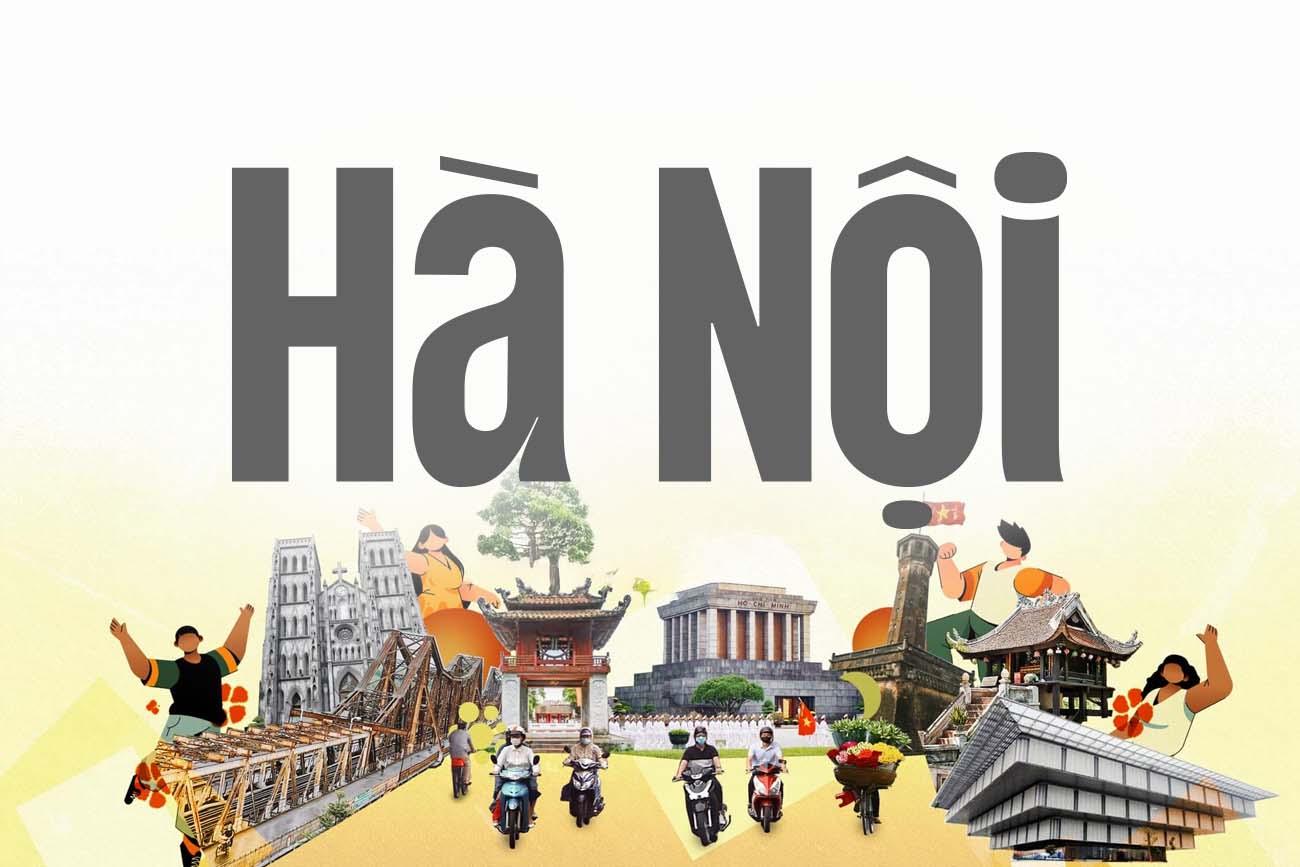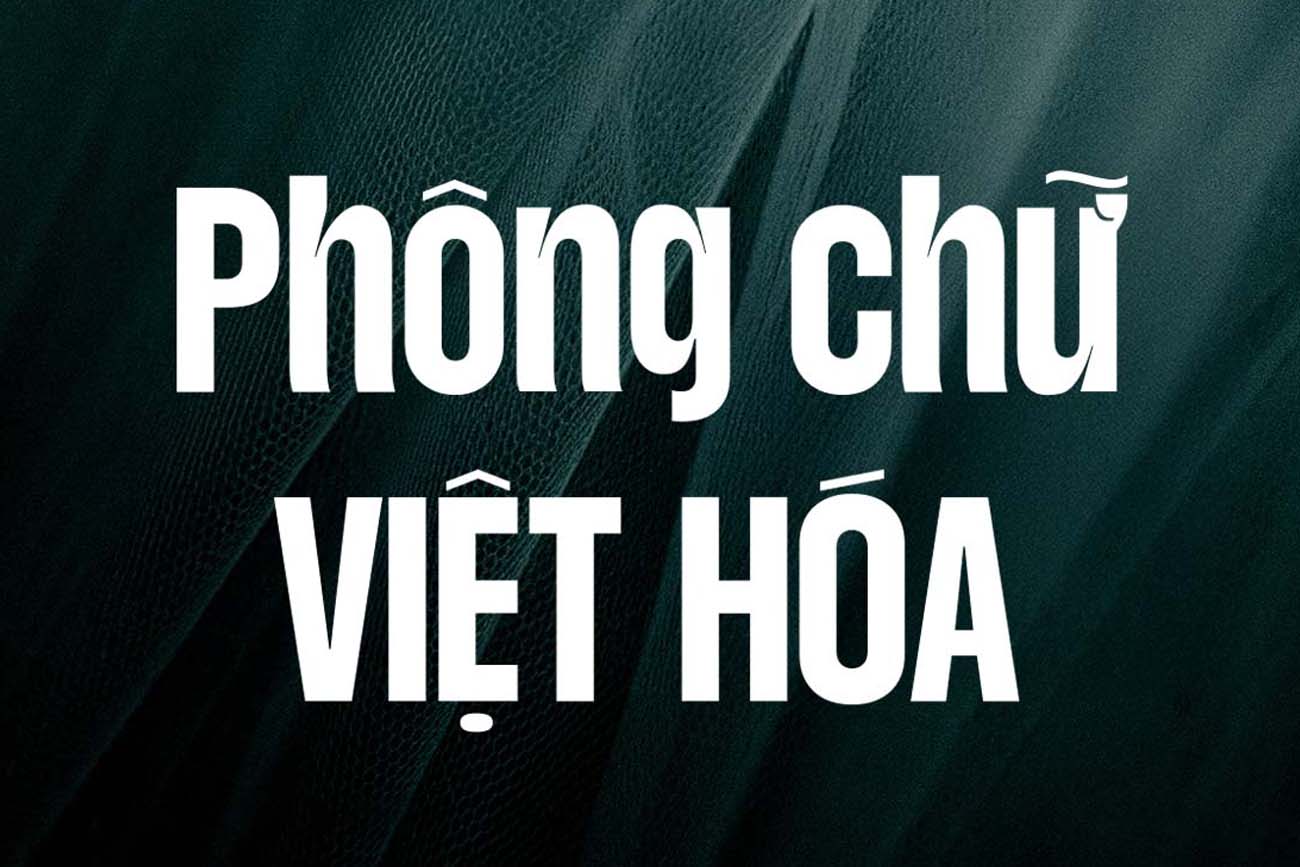
Font chữ cứng cáp Việt hóa SVN Gratelos Display Regular
Tác giả Stringlabs
Việt hóa Team SVN
Bạn đang tìm kiếm một font chữ hiện đại, mạnh mẽ và hỗ trợ đầy đủ tiếng Việt để sử dụng cho tiêu đề, poster hay logo thương hiệu? Font SVN-Gratelos Display Regular chính là lựa chọn hoàn hảo cho mọi thiết kế cần sự ấn tượng và rõ ràng.
Nguồn gốc font chữ Gratelos là gì?
Gratelos Display là một kiểu font sans-serif display được thiết kế bởi Stringlabs Creative Studio – một đơn vị đến từ Indonesia, nổi bật với những font chữ mang cá tính mạnh. Gratelos mang tinh thần thiết kế hiện đại, tập trung vào hình khối rõ ràng và độ dày đồng đều, rất phù hợp với xu hướng tối giản trong thiết kế đương đại.
Phiên bản SVN-Gratelos Display Regular đã được Việt hóa hoàn chỉnh bởi SVN Fonts, giúp bạn sử dụng font một cách mượt mà trong các dự án sử dụng tiếng Việt mà không lo lỗi dấu.
Đặc điểm nổi bật của font chữ Gratelos
• Kiểu chữ: Sans-serif, Display
• Phong cách: Mạnh mẽ, tối giản, hình học hiện đại
• Thiết kế: Chữ cái được tối ưu theo tỉ lệ hình học, góc bo nhẹ, tạo cảm giác vừa cứng cáp vừa thân thiện
• Khả năng đọc tốt ở cả kích thước lớn và nhỏ
Hỗ trợ tiếng Việt & Việt hóa
Phiên bản do SVN Fonts Việt hóa đã được tinh chỉnh đầy đủ bộ dấu tiếng Việt theo đúng tỉ lệ và phong cách gốc. Nhờ vậy, bạn hoàn toàn yên tâm sử dụng trong văn bản dài, không bị lỗi hiển thị hay thiếu dấu.
Font chữ Gratelos Việt hóa là lựa chọn lý tưởng cho những ai yêu thích phong cách hiện đại, mạnh mẽ và tối giản. Với khả năng tương thích cao và hỗ trợ tiếng Việt hoàn chỉnh, font này sẽ giúp bạn nâng tầm thiết kế trong mọi dự án sáng tạo.